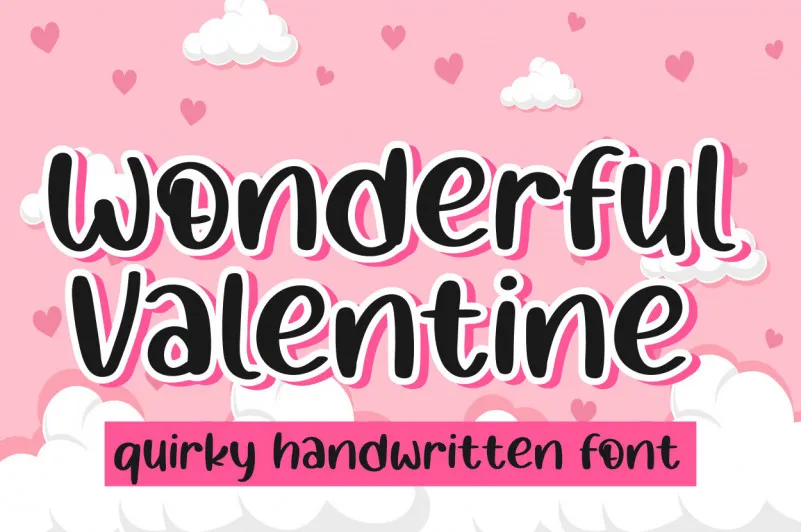
Wonderfull Valentine Font – Download Grátis
A Wonderfull Valentine Font é uma fonte escrita à mão simples e amigável que traz alegria para qualquer design. Com seu tom leve e ligeiramente quirk, essa font ajudará você a dar um toque encantador e divertido em todos os seus projetos. Se você for confiante ao adicioná-la às suas criações, garantirá que o resultado final será algo que você irá amar. Esta font é perfeita para aqueles momentos especiais de amor, como datas comemorativas ou presentes personalizados. Não apenas uma fonte de amor romântico, ela também combina a simplicidade e a delicadeza da escrita à mão para criar um design encantador que você definitivamente vai querer usar.